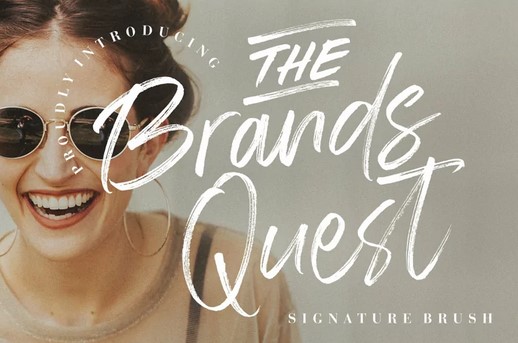
Fontbundles The Brands Quest Signature Brush Font
[Fontbundles] The Brands Quest Signature Brush Font
Brands Quest - это фирменный шрифт с текстурированной кистью, который может войти в вашу коллекцию.
The Brands Quest идеально подходит для брендинговых проектов, логотипов, свадебных дизайнов, постов в социальных сетях, рекламы, упаковки товаров, дизайна продуктов, этикеток, фотографий, водяных знаков, приглашений, канцелярских принадлежностей и любых проектов, где нужен вкус почерка.